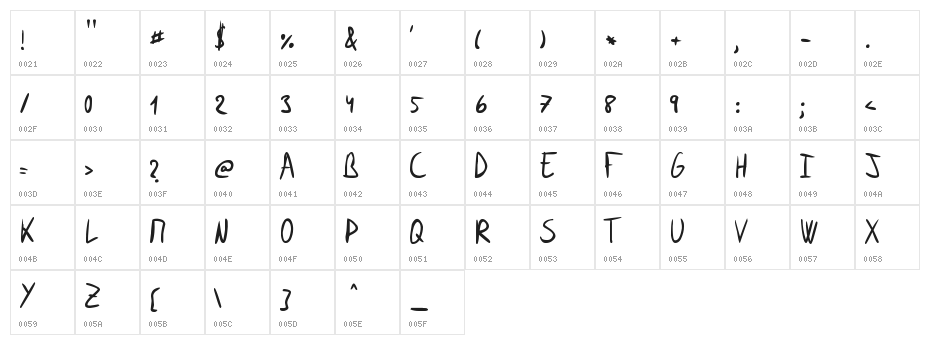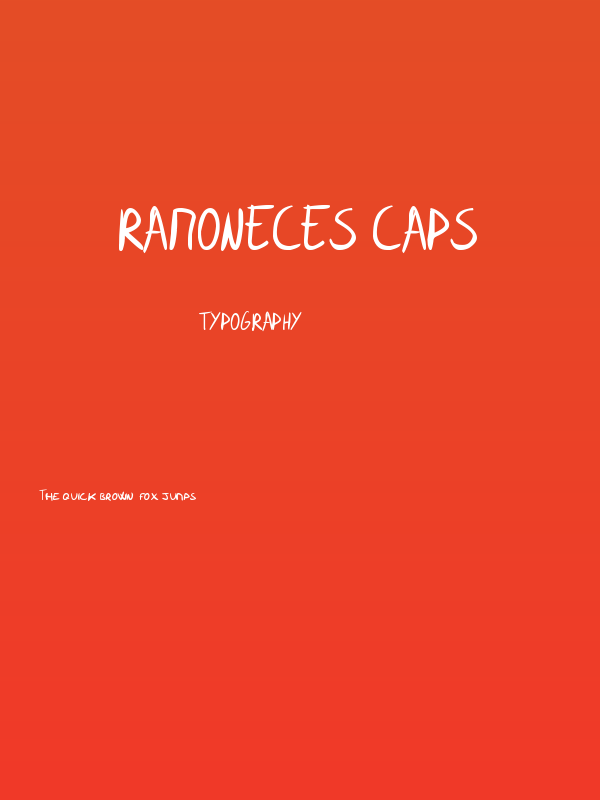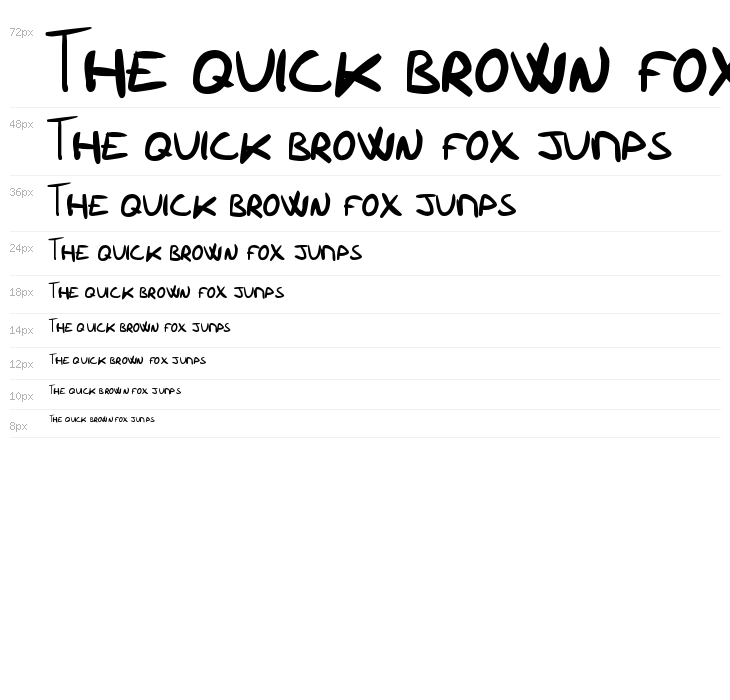
Ramoneces caps Font
| Progetti proposti | Perfect for posters, album covers, branding for creative industries, and any project needing a personal, dynamic touch. |